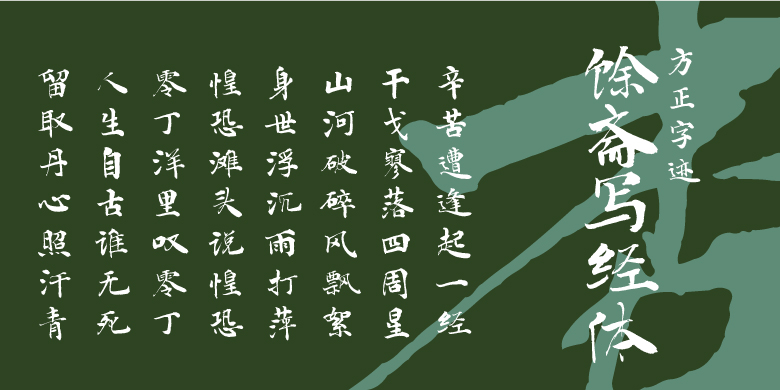
方正字迹-馀斋写经体
方正字迹-馀斋写经体,这款字体结构工整、笔画清晰,兼顾美观与易读性,适用于标题、正文、海报、包装、LOGO 等多种场景。字形优雅稳定,风格百搭耐看,适配日常排版与创意设计,让文字呈现更舒适、更具质感。方正字迹-馀斋写经体一笔一画,皆是细节,以均衡的比例、流畅的线条打造舒适视觉体验,字形端正大气,风格简约现代。无论是商业设计、品牌宣传还是日常排版,都能轻松驾驭,让文字更有格调与力量。方正字迹-馀斋写经体字体下载。
以二王为根基,广收博取,草情隶意寓于敦煌写经之中,并以之雅化。形成其清逸俊秀的书风。